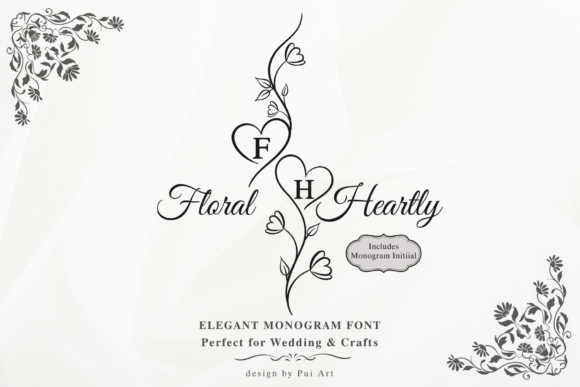
Floral Heartly Monogram
適切なデザイン要素を見つけるのは難しい場合がありますが、Floral Heartly Monogramは作品を即座に引き立てる優れたコレクションを提供します。
POD(オンデマンド印刷)製品、結婚式の招待状、またはソーシャルメディアのグラフィックを作成している場合でも、Floral Heartly Monogramは理想的です。